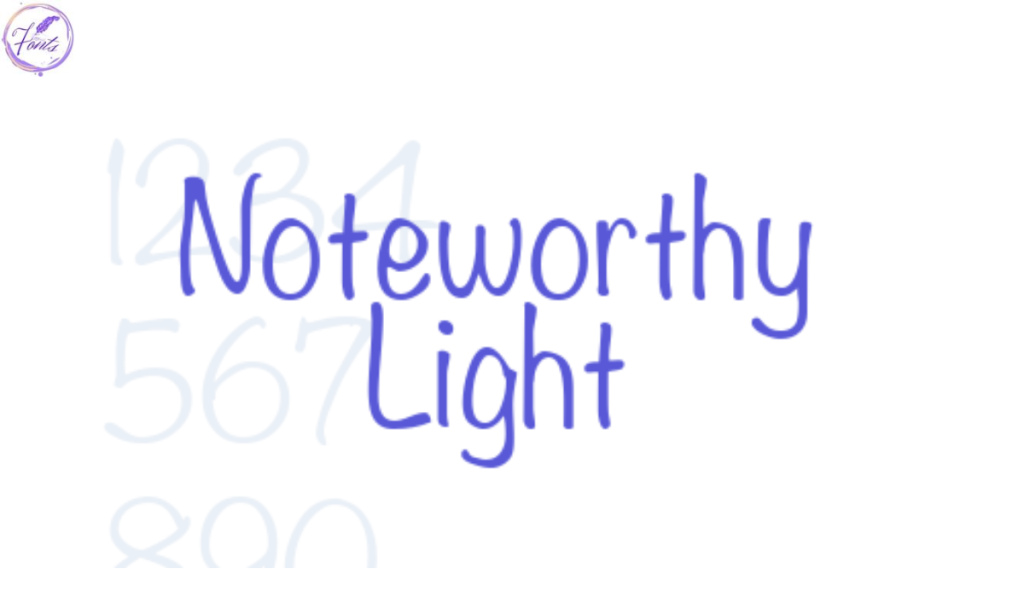
Font 1FTV Noteworthy Light font việt hóa
Tác giả: Emily Spadoni
Ngày phát hành: 2011
Ngôn ngữ: Tiếng Việt và một số ngôn ngữ khác
Bộ Font: Noteworthy
Phân loại: Cá tính, Độc đáo, Hiện đại
Kiểu chữ: Kiểu chữ viết tay (script)
Độ dày: Light
Noteworthy light font là một bộ font thanh mảnh và tinh tế, mang lại cảm giác nhẹ nhàng và thoải mái cho người đọc. Được thiết kế bởi các chuyên gia hàng đầu trong lĩnh vực typography là Emily Spadoni, font này ra mắt lần đầu vào năm 2011 và nhanh chóng được yêu thích bởi sự thanh lịch và dễ đọc.